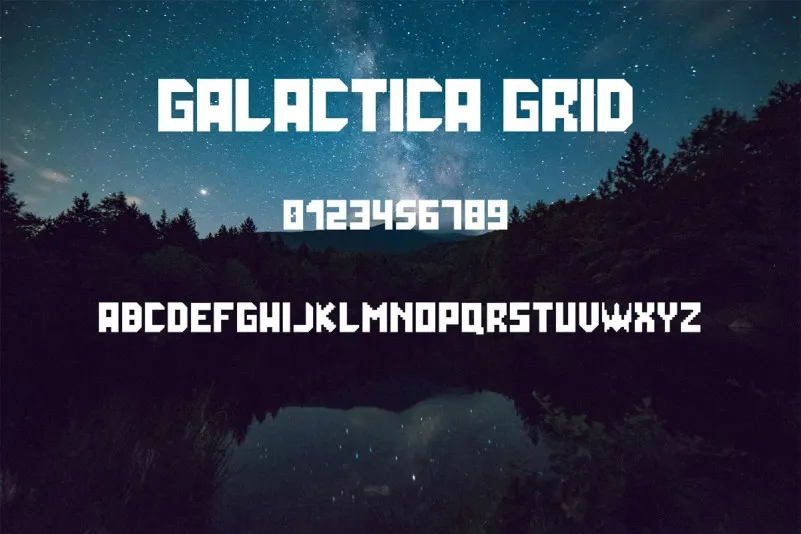
A Galactica Grid Font é uma tipografia futurista afilada e limpa, projetada pelo designer vladocar. Perfeita para aplicações visuais que exigem impacto visual agressivo e ressaltos criativos, como logomarcas, embalagens, convites de festa ou até mesmo t-shirts. Além disso, a Galactica Grid Font é ideal para gráficos em tela cheia e websites, trazendo um toque único que tornará qualquer projeto uma verdadeira obra-prima. Seja você criando uma camiseta personalizada ou montando seu site, essa fonte será o recurso perfeito para destacar seus designs de maneiras nunca antes vistas.